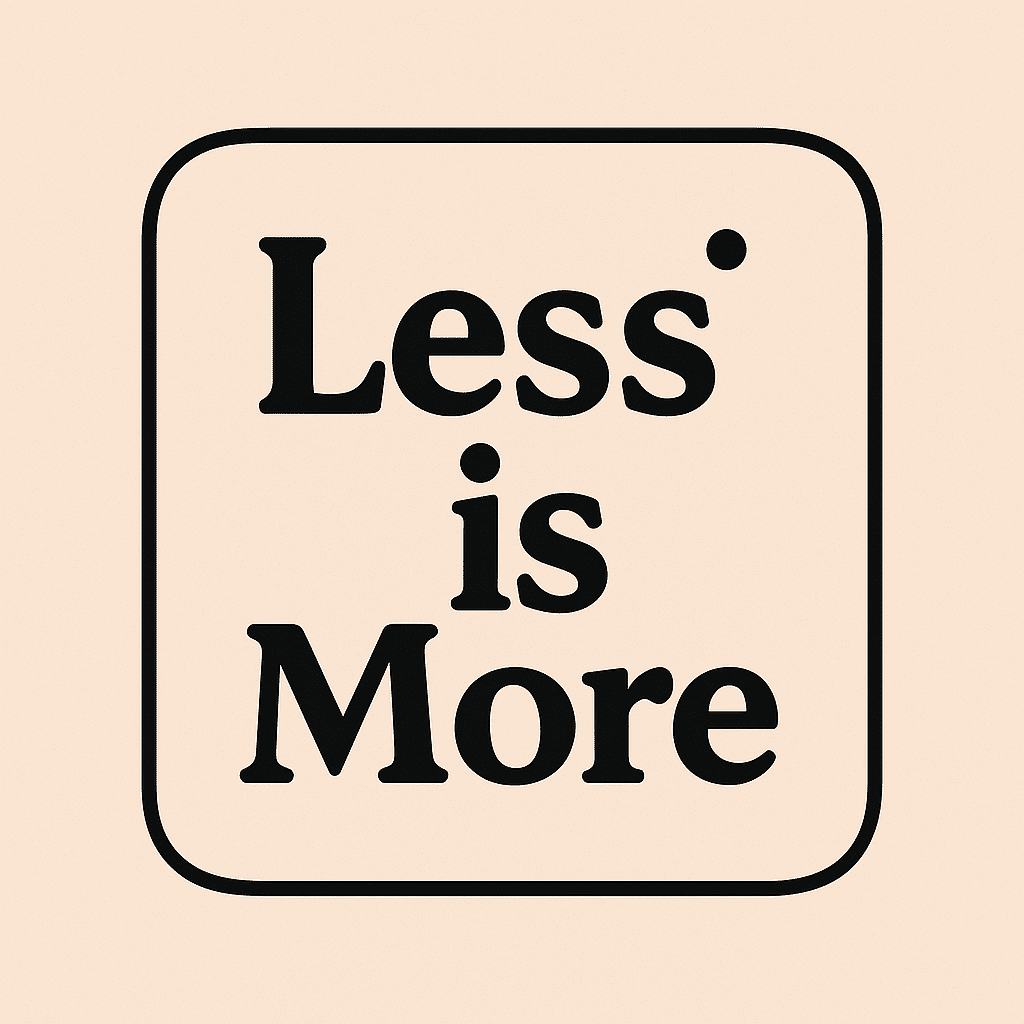
בחירת הפונט הנכון היא שלב קריטי בעיצוב גרפי. היא משפיעה על קריאות הטקסט, על התרשמות הקהל מהעיצוב ואף על המסר אותו מעוניינים להעביר.
למרות החשיבות הרבה שיש לבחירת הפונטים המדויקים, מעצבים מתחילים נוטים לעשות מספר טעויות נפוצות בבחירת הפונטים.
לפעמים הם מתבלבלים מההיצע הרחב של פונטים מיוחדים בעברית, לעיתים משלבים כמות פונטים גבוהה מדי, ולפעמים בוחרים פונטים שלא משתלבים זה בזה. במאמר זה נסקור את הטעויות השכיחות ביותר ונציע פתרונות.
הרצון של מעצבים להתבלט ולהעניק לעיצוב שלהם טאצ' ייחודי הוא רצון מובן מאד, ולעיתים הוא מוביל לבחירה בפונטים מיוחדים מאוד, ואף לא שגרתיים, כאלה שתמיד שמים אליהם לב ומעניקים אופי מיוחד למוצר המוגמר.
אך בעוד שפונטים מיוחדים בהחלט יכולים להוסיף עניין לעיצוב, שימוש יתר בהם עלול להקשות על הקריאה משמעותית, ולהפוך את העיצוב למסורבל ולא נעים לעין.
חשוב מאוד למצוא את האיזון הנכון בין ייחודיות ויופי לבין בהירות וקריאות, כיוון ששני הדברים האלה חשובים ביותר.
זה אמנם נחמד ביותר שהרשת היום מוצפת יצירות יפהפיות ומציעה מגוון מרהיב של פונטים בעברית להורדה, הן בתשלום והן בחינם. אבל חשוב מאוד לזכור שלא כל פונט מתאים לכל פרויקט.
לפני שאתם מורידים פונט, בדקו קודם כל את האיכות שלו, עיינו לעומק בתנאי השימוש בו, ומעל לכל – בחנו היטב את ההתאמה שלו לסגנון העיצוב שלכם, ולתוכן אותו אתם מעצבים.
אחד מכלי העיצוב הכי פופולריים היום, אחד מיני רבים, הוא קנבה, תוכנה שמאפשרת לעצב בקלות ובלי הרבה ניסיון, ולהוציא תוצרים יפים על ידי היצע רחב של טמפלטים והתאמה של תבניות מעוצבות מראש. אבל המלאי של פונטים בעברית בקנבה מצומצם ביותר.
לסיכום, בחירת הפונט הנכון היא מיומנות חשובה ביותר עבור לכל מעצב. על ידי הימנעות מהטעויות הנפוצות שסיפרנו לכם עליהן כאן והקפדה על בחירת פונטים שמתאימים לסגנון העיצוב ולמטרת המסמך – אנחנו סומכים עליכם שתוכלו ליצור עיצובים מקצועיים ומושכים יותר.
שילוב בין מספר פונטים יכול להעניק עניין לעיצוב, אך יש לעשות זאת בזהירות. בחרו פונטים המשלימים זה את זה ומשתלבים זה בזה, והקפידו ביניהם על היררכיה טיפוגרפית ברורה. לדוגמה: אל תשתמשו עבור פסקה רגילה באותו הטקסט שמופיע בכותרת, אל תחליפו טקסטים בין פסקה לפסקה כדי לשמור על אחידות, ועוד.
קריאות הפונט היא אחד הגורמים המכריעים בבחירת פונט. פונט קשה לקריאה עלול לגרום לקהל היעד להתעלם מהטקסט. בחרו פונטים ברורים וקלים לקריאה, במיוחד אם וכאשר מדובר בטקסטים ארוכים.
שימוש במספר מצומצם של פונטים בעיצוב אחד הוא עיקרון בסיסי בעיצוב גרפי טוב. שימוש במגוון רחב מדי של פונטים יכול ליצור עיצוב רועש, קשה לקריאה ומבלבל: